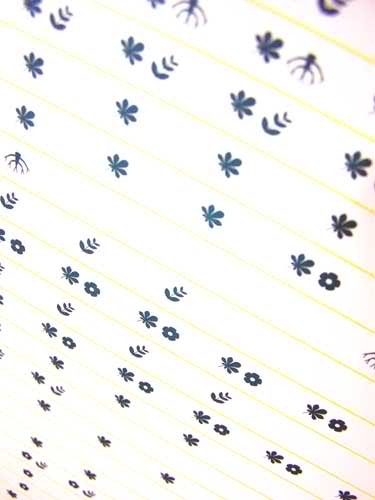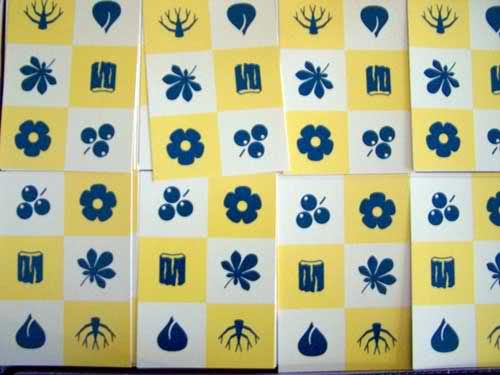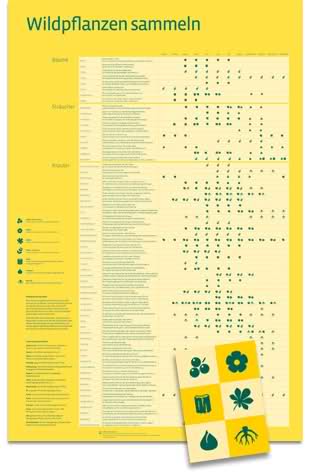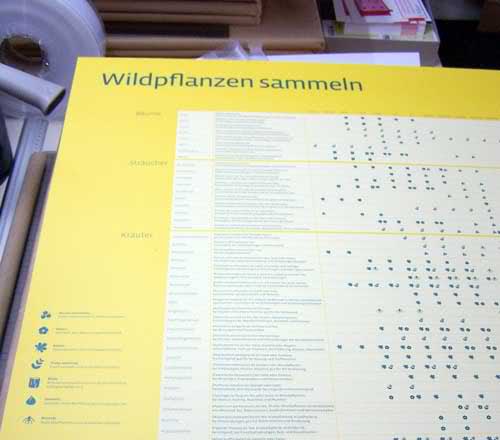
Neues Lernplakat ist da!
wieder will ich typografie.info als erstes Forum nutzen, um das neue Lernplakat anzukündigen. Am Freitag kamen sie aus der Druckerei, noch kräftig nach Farbe riechend. Mittlerweile sind sie etwas ausgedünstet und fertig zum Versand.
Da liegen sie!
Piktogramme ohne Ende
Diesmal geht es um Wildpflanzen und deren Nutzen für die Hausapotheke. 64 Kräuter, Sträucher und Bäume werden vorgestellt und wann welche Pflanzenteile am besten gesammelt werden.
Gesetzt ist das Plakat aus der wunderbaren VistaSans von Xavier Dupré, die hier zeigen kann, dass sie im Lesetext genauso gut geht wie in Überschriften.
Dazu gibt es wie immer eine passende Postkarte zum Sammeln, Tauschen, Liebhaben.
Das nächste Plakat geht übrigens wieder in die Chemie.